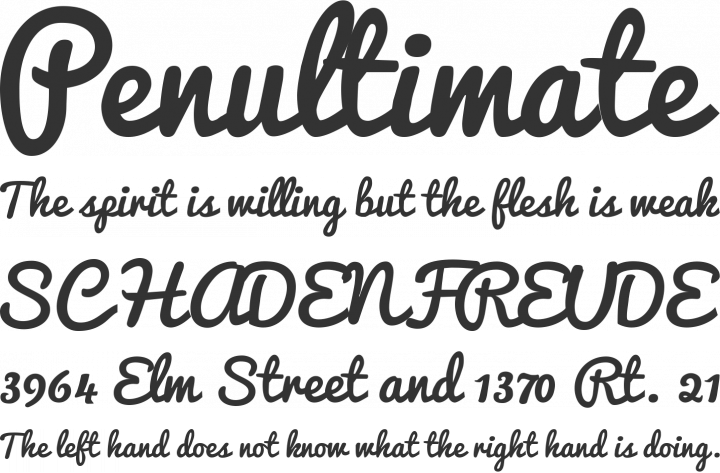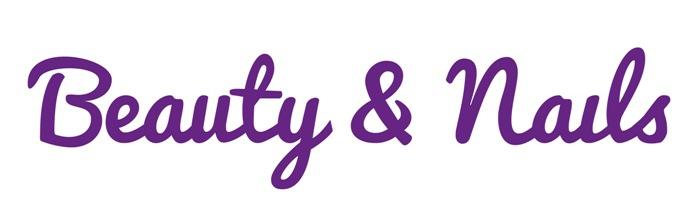
Handwriting Schrift gesucht (Beauty & Nails)
kann mir jemand bei der Suche nach der folgenden Schrift helfen?
Vergiss beim Nachbauen aber bitte nicht den i-Punkt! Im Englischen gibt es eine Redewendung:  dot your i’s and cross your t’s. Wer das macht, ist sorgfältig; wer nicht, nachlässig. Und gerade bei solch einer angelsächsischen Schreibschrift, bei der man die kleinen Ts tatsächlich quasi durchstreichen muss, fällt es dann evtl. auf, wenn etwas unterlassen wurde, das angelsächsischen Grundschülern eingeimpft wird. Sonst passiert es eben schnell, dass Nelson auf Europabesuch mit dem Finger auf den Laden zeigt und lacht: »Haha, you didn’t dot your i!«